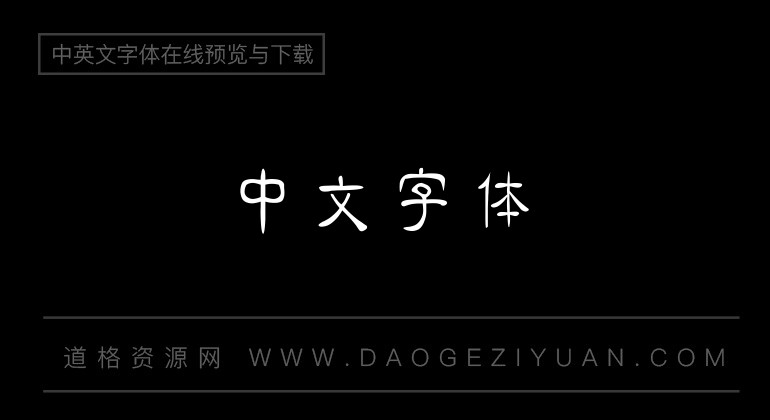
金梅中隶原体国际码字体是一种由汉字起源的字体,它是由中国的汉字研究专家张梅编写的,它由简体中文书写系统组成,主要用于繁体中文书写系统。它采用汉字的标准字形,并将其结合国际码的特点,使其具有更好的可读性和可书写性。金梅中隶原体国际码字体可以在多种操作系统上使用,包括Windows、Mac OS、Linux等,并可以在多种文档格式中使用,如Word、Excel、PDF等。文件名:JinMeiZhongLiYuanTiGuoJiMa-1.ttf
金梅中隶原体国际码是一款非常不错的手写艺术字体,具有很好的视觉感,适合于文化类的宣传设计、商业类品牌的广告和产品包装设计以及个性化文字排版等较多场景。